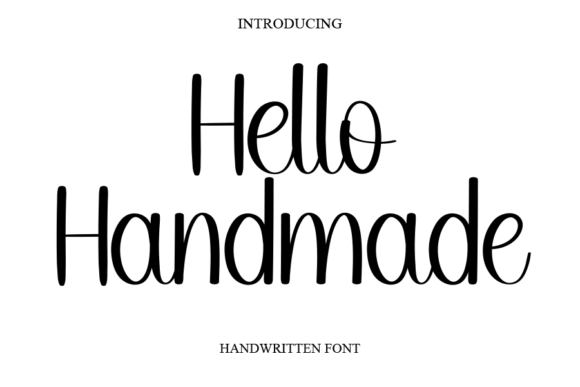
Hello Handmade
Hello Handmadeのような高品質の素材をお探しの場合、このプレミアムパッケージはクリエイティブなプロジェクトに素晴らしい選択です。
精密に作られたHello Handmadeは、クリーンなベクター、滑らかなタイポグラフィ、そして安心のための商用ライセンスを提供します。
POD(オンデマンド印刷)製品、結婚式の招待状、またはソーシャルメディアのグラフィックを作成している場合でも、Hello Handmadeは理想的です。